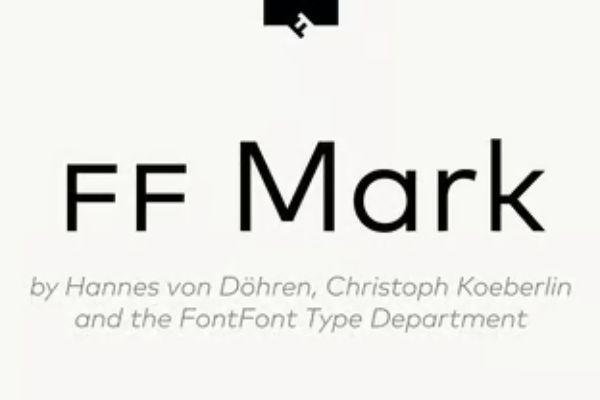
FF Mark® Pro Black
FF Mark 设计灵感来源于包豪斯传统几何无衬线字体,满足现代通信的需求。它应用范围非常灵活,适合于电影电视、广告和包装、编辑出版、logo、品牌、软件和游戏、网页和屏幕设计。FF Mark 的 W1G 版本具有泛欧洲字符集,支持西欧、东欧和中欧几乎所有基于拉丁字母的流行语言 / 书写系统,以及一些基于西里尔字母和希腊字母的语言 / 书写系统。